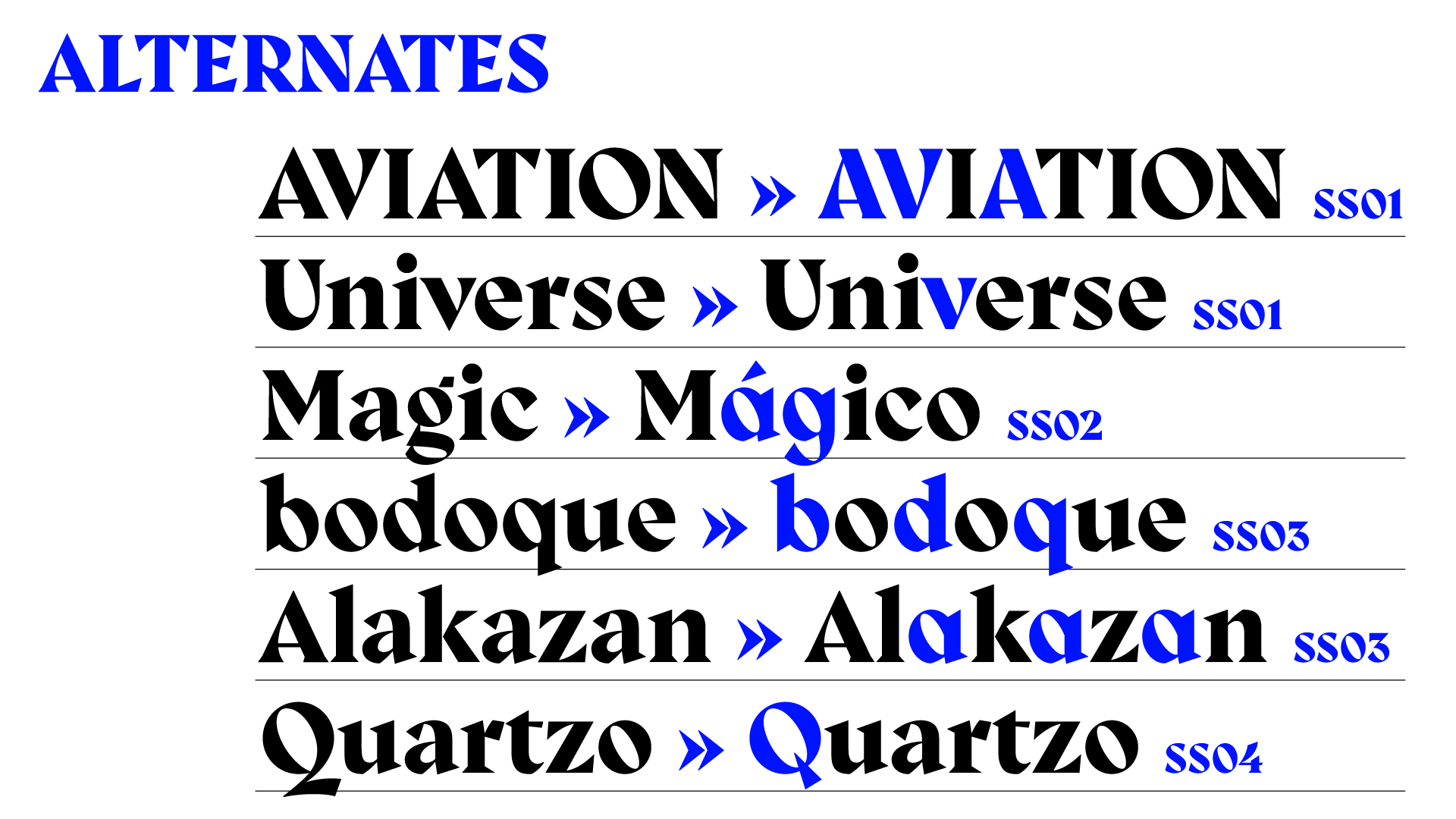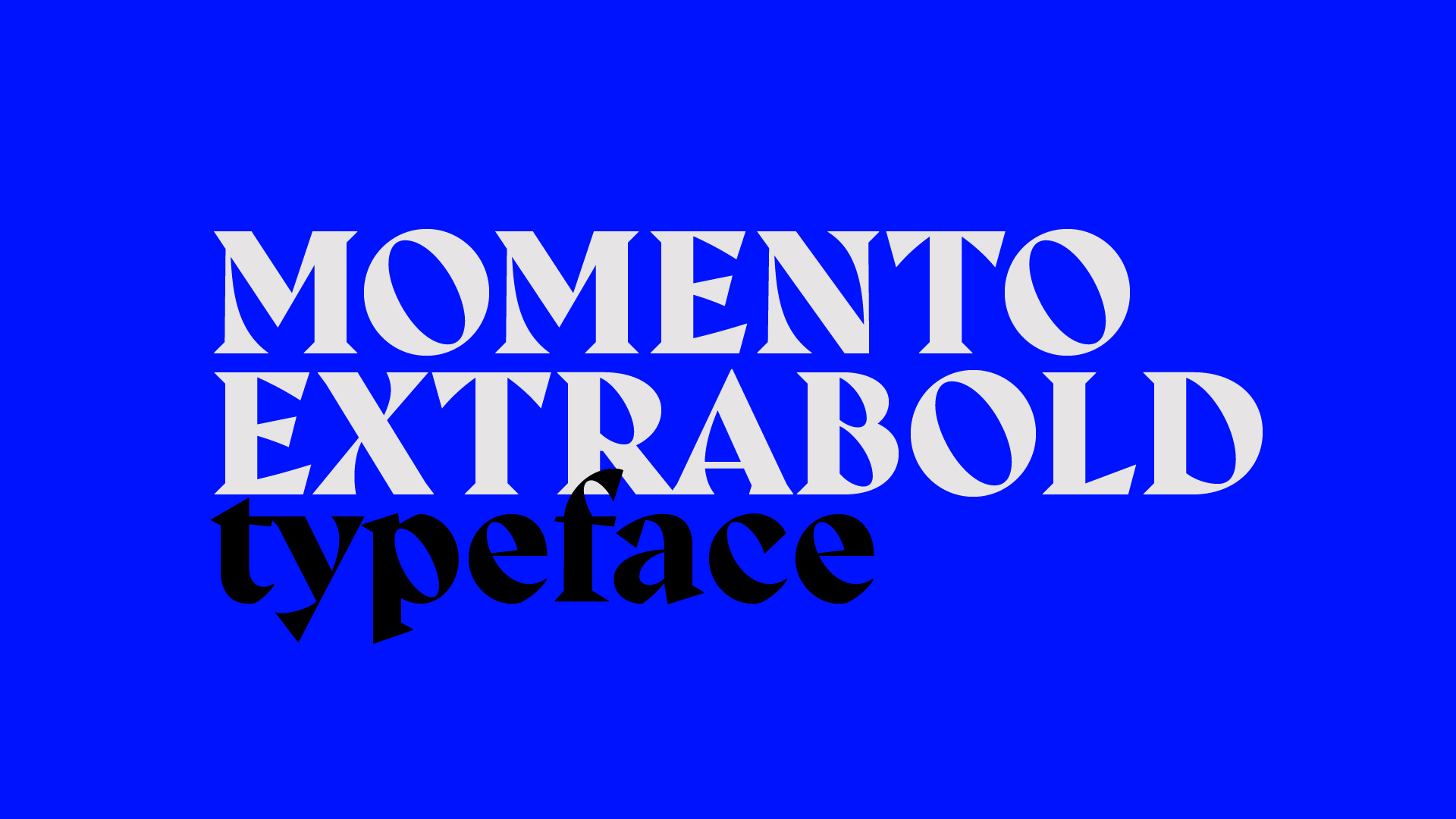
Tipo Aquilo #92 – Andróides sonham com ovelhas azuis?
Reflexões sobre o designer e o criativo no mundo do algoritmo
Vocês lembram do do troca-troca de cartas entre escritores de newsletters? Ela está indo para a terceira edição, e o Tipo Aquilo desta semana é uma carta para uma das pessoas da comunidade. Mais especificamente, a
, autora, colunista no Delirium Nerd e produtora da newsletter . Mais uma vez, não fiquem acanhados, achando que estão lendo conversa dos outros; apesar de ser uma carta, a ideia é pegar um texto escrito pela Bia e continuar falando de tipografia com base nesse texto. Então, novamente, fique à vontade e aproveite esta penúltima edição do ano.Olá, Bia. Tudo bem com você? Espero que 2024 tenha sido um ano gentil contigo, e que 2025 seja generoso apesar de estarmos todos cronicamente online assistindo a muitos apocalipses ao mesmo tempo. Todos, menos a Jout Jout, mas não vou entrar nesse assunto agora. Primeiro, eu vou subverter uma regra do amigo secreto, que reza sobre pegar um texto da pessoa e discorrer sobre ele. Aqui, eu vou passear por algumas edições que você escreveu ao longo do ano pra escrever uma porção de coisas que talvez façam sentido no final. O motivo dessa subversão é que não tem como dizer que apenas um texto seu foi significativo nesse ano… aliás, vocês que não são a Bia e se importam com textos e reflexões oportunas sobre a vida online contemporânea, vão lá e assinem o Ovelha Azul.
Além de designer e tipógrafo, eu sou programador front-end. Há alguns anos, me definiria também como um entusiasta de tecnologia; só que esse mesmo mundo tem me deixado mais amargo com o tempo. Lembra quando várias big techs mudaram de marca para logotipos mais simples, com letras que prometiam mais “humanidade” para suas marcas? Só que, a partir daí, elas tornaram-se mais ferozes em seus movimentos anti-regulação e anti-concorrência, e colocaram dezenas de profissões e milhões de seres humanos vivendo em função das respostas binárias do tal do algoritmo. Geralmente, esse aqui é um espaço pra falar do mundo a partir do ponto de vista do design, do designer e — minha nerdice mor — da tipografia; só que o designer não está num lugar protegido nessa época do capitalismo tardio, Bia. Essa edição/carta tenta colocar essa classe dos designers junto a outras que estão perdidas nesse tiroteio global de algoritmos.
“The Corporation” (2003) é um documentário antigo, mas ainda longe de ser datado. Ele mostra como várias corporações usam um entendimento jurídico norte-americano de que pessoas jurídicas compartilham de direitos e proteções similares às de pessoas físicas. Com esse subterfúgio, elas praticam atos deliberados de ataque ao meio-ambiente, comunidades e o próprio sistema econômico, de forma a maximizar lucros e dividendos para acionistas. No final, ao compararmos as corporações com pessoas, elas mostram-se pessoas horríveis, que precisam de interdição para ontem… só que elas são empresas, então não podem ser interditadas porque… são pessoas. Desde então, tentamos dormir com essa contradição no ar, e o refinamento na arte de personalizar e despersonalizar corporações só tem aumentado.
Uma dessas táticas é o algoritmo, enquanto buzzword. Um algoritmo é nada mais que um conjunto de instruções para fazer algo e ter algum resultado. Sabe o caderno de receitas da sua avó? Cada receita é um algoritmo: pegue os ingredientes, faça cada passo certo e voilá, sua comida gostosa está pronta. O grande, robusto e sofisticado algoritmo, para o qual milhares de pessoas vivem em função, é uma série de condicionais para que algo seja (ou não) visto por você, baseadas no que as plataformas acham que você se interessa e em outros atributos definidos pelas próprias plataformas. Esses atributos podem existir para atender interesses externos (legislações e outras externalidades) e as regras das próprias plataformas. No fim, a novidade — que não é novidade — é que o trabalho de designers, publicitários, creators e artistas em redes sociais passa por um grande beija-mãos do que as próprias plataformas entendem como apropriado, bonito e moderno. Isso é algoritmo, o bode expiatório com que as redes sociais se despersonalizam quando necessário.
O tal do “algoritmo” não é uma consciência ou inteligência suprema, mas ele matou o mainstream. Ok, não o algoritmo sozinho; nesse caso, entenda algoritmo como o poder de influência das big techs na vida pessoal de 5,1 bilhões de habitantes do país Internet. A algoritmo criou 5,1 bilhões de formas diferentes de digerir a infinidade de conteúdo criado diariamente, ao ponto de que nenhum produtor de conteúdo que se preza cria para apenas uma plataforma. Citando a Bia, “não podemos mais falar de um grande rio principal, indubitavelmente sendo consumido por todos. A TV segue forte, mas ela mesma se adaptou a esse cenário: trechos de programas rodando pelas redes, interação ao vivo com comentários online, absorver estrelas nativas da internet”. Manter coerência e autenticidade do discurso, e a capacidade da pessoa reconhecer algo ou alguém entre algoritmos diferentes, tornou-se algo desejável entre artistas, profissionais criativos e marcas que não são plataformas.
E isso é um ponto a favor de quem não tenta ser um profissional algorithm-driven, um título maneiro de ostentar no LinkedIn, mas que não significa ser, de fato, alguém resolvendo um problema mais profundo do que exposição e alcance, ou lidando com mais do que grandes caricaturas das pessoas por trás de seus perfis. Nossas ferramentas clássicas de trabalho, como a pesquisa, o rascunho de ideias, a validação com usuários finais, seguem mais importantes do que olhar para o que um algoritmo aprova ou não. Todas as versões dos algoritmos, as que já passaram e as que entraram no lugar fazendo promessas não cumpridas de que você veria mais dos seus amigos, têm algo em comum: elas olham para o passado. Elas sabem o que uma pessoa fez, disse, como reagiu a um estímulo, mas elas trabalham sempre com o passado; sais pas, com uma versão reducionista do passado alheio.
É nesse ponto que um texto recente da Bia, sobre a anatomia da subversão, entra em consonância com um texto recente de outra escritora, a type designer Keya Vadgama, em que ela manifesta seu descontentamento em ter que criar conteúdo e até estratégia pensando em engajamento. Como se não bastassem seus requisitos inatos, as “sugestões” para conseguir likes e shares fazem a tarefa de criar projetos pessoais e corporativos ainda mais difícil. Chega ao ponto de que a coisa mais subversiva que um designer possa fazer para si é… esquecer o algoritmo. Testar possibilidades baseando-se na intuição, no que uma boa biblioteca de livros e referências, e no que a experimentação por livre e espontânea vontade podem oferecer. De novo, citando a Bia, “em um mundo online, subversivo acontece fora da tela”.
Ainda em sintonia com a onda de fazer mais coisas baseadas em feeling, ou confiar no próprio taco, o Toronto Design Directory fez há algumas semanas a décima edição do Cool Concept, um evento que chama designers para apresentar casos de sucesso de coisas que eles fazem para si, sem ser para um cliente. Existir dez edições do Cool Concept ajuda a mostrar duas tendências bem interessantes: a de que muita gente quer fazer coisas legais, fora do escritório e das limitações impostas por clientes; e a de que muita gente se interessa mais por isso, na verdade. Assumir-se ingenuamente como uma pessoa que quer fazer coisas legais, antes de designer, escritor, publicitário ou qualquer outra profissão, é o que motiva pessoas a fazerem coisas legais, que tiram o mundo da mesmice. Fazer coisas legais significa olhar para si, para uma existência completamente diferente das caricaturas feitas por andróides de algoritmos, e mais completa de substância. Não a daquele filme, isso fica pra outro dia…
Tendo dito tudo isso, tenho duas coisas a dizer.
Primeiro: Bia, eu sei que você faz um monte de coisas, e espero que todas elas sejam legais pra você como é o Ovelha Azul. Não foi a coisa mais fácil do mundo escrever pra você, porque quase todo texto seu tangencia algo importante para o universo criativo. Não tinha como escolher só um texto, então espero que tenha gostado dessa pequena costura. (=
Segundo: cumprindo a segunda parte do troca-troca de newsletters, a minha recomendação, que ilustra essa edição, é o artista brasileiro Alvaro Naddeo, nascido em São Paulo, morando atualmente em Los Angeles. A Bia sempre destaca um artista diferente em cada edição, então eu fiz algo similar, que destaca as belas aquarelas de Naddeo num contexto distópico atual.
🔗 Link: Plau Type Trends 2025, uma análise de tendências tipográficas da turma do estúdio brasileiro Plau para o próximo ano.
🇧🇷 Fonte brazuca: Momento Display, de Dan Schunck.